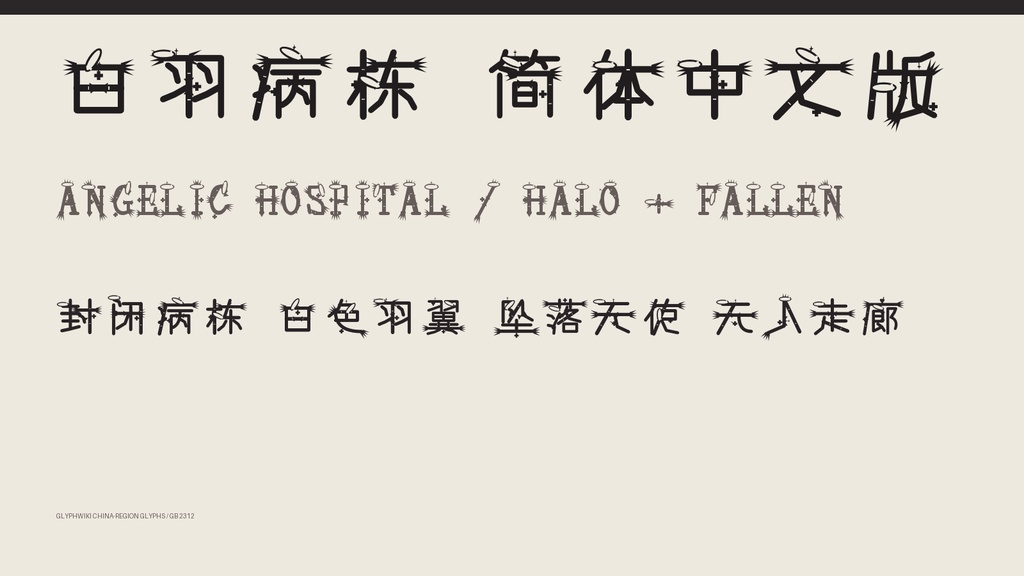
白羽病栋 SC|简体字6,763字・2款字体
【白羽病栋 SC / SHIROHANE BYOTO SC】 洁白羽翼落入封闭病栋,破损光环与医疗标记附着在文字之上。 这是一套结合病院、天使与颓废恐怖意象的简体中文展示字体。 Halo 保留冷白、安静的神圣感,Fallen 则加入更明显的破损与堕落气息。 ■ 价格 1,680日元 ■ 内含字体 ・Halo:羽翼与光环构成的冷静版本 ・Fallen:裂损、坠落与病栋感更强的版本 ■ 格式 TrueType(TTF)2款 / Windows・macOS ■ 收录 每款共7,542个字码(包含空格) GB 2312 全部汉字:6,763字 拉丁字母、数字、半角与全角符号:779个 ■ 特点 ・羽毛、光环、医疗符号与裂损细节 ・圣洁与不安并存的两种风格 ・汉字、英文字母、数字和符号保持统一世界观 ・适合冷色、白色与低饱和视觉设计 ■ 推荐用途 医院恐怖、暗黑天使、悬疑游戏、小说封面、音乐封面、角色标题、影视字幕、海报、直播画面与标志 ■ 使用许可 可用于个人及商业项目。可用于标志、视频、游戏、印刷品、直播素材、同人及商业作品。 无需署名。禁止重新分发、共享或转售字体文件。 详细条款请查看ZIP内的使用许可。 ※含有羽毛与破损细节,推荐用于28px以上的标题。